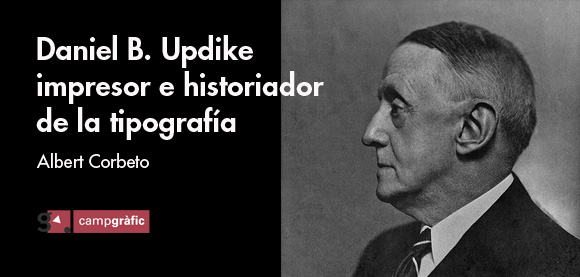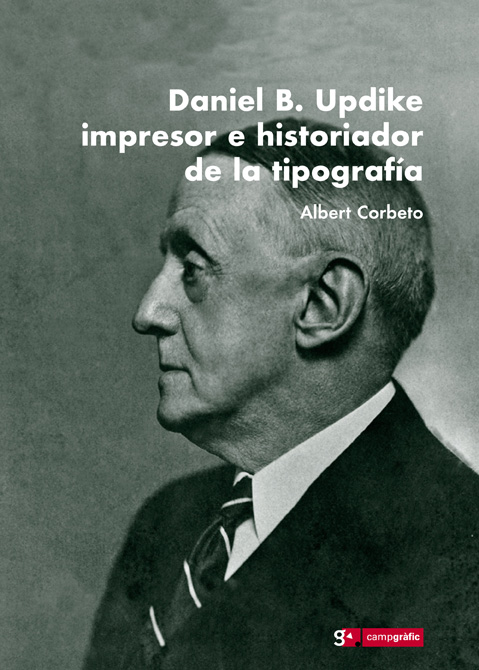
El investigador e historiador de la tipografía Albert Corbeto ha publicado en la Editorial Campgràfic sus dos últimas obras: Daniel B. Updike impresor e historiador de la tipografía y Tipos de imprenta en España. La primera reflexión que se me ocurre es la de que ver el nombre de Updike en la portada de un libro en castellano dice mucho del estado actual e interés creciente de los estudios sobre la historia de la tipografía.
Además Campgràfic ha «tirado la casa por la ventana» y ha puesto en el mercado las dos obras de forma conjunta e inseparable posibilitando apreciar de manera más nítida la importancia del trabajo de Corbeto en el panorama de la investigación histórica sobre nuestro pasado tipográfico. En esta entrada vamos a comentar el libro de Updike dejando para una próxima el que versa sobre los tipos de imprenta en España.
Para todos aquellos que se han interesado por la historia general de los tipos de imprenta, el nombre de Daniel B. Updike remite inmediatamente a una de las «biblias» de la materia su monumental obra Printing types. Their history, forms and use publicado por primera vez en el año 1922. La extensión de la misma, que abarca en sus contenidos centrales la producción tipografía de los principales países europeos desde el periodo incunable hasta el siglo XIX, es de una riqueza y de una utilidad que bien podemos suscribir la idea expresada por Robin Kinross en su Imprenta moderna de que «En lo que respecta a los historiadores de la tipografía, se puede decir que hay un antes y un después de Updike».
En la edición que nos ocupa, el autor ha incluido la traducción literal de los dos capítulos dedicados a los tipos españoles y, lo que a nuestro juicio dota a la misma de un gran valor, tres ensayos en los que Corbeto pone en contexto la obra del norteamericano en toda su extensión enfocando tanto su producción propia en la Merrymout Press como su labor como historiador de la tipografía.
El primero de ellos lleva por título Daniel B. Updike el impresor erudito, y en el mismo el autor nos detalla su biografía desde su nacimiento y sus primeros pasos en el mundo de la imprenta hasta llegar a su consolidación como impresor de renombre. Con un acercamiento crítico a su obra que repasa sus influencias y la evolución de su estilo, el ensayo nos sumerge en el apasionante momento en el que las máquinas irrumpen en los talleres de imprenta a finales del siglo XIX y las poderosas fuerzas que desataron, tanto a favor como en contra, en el mundo editorial. A través de la aptitud de Updike al respecto, Corbeto nos pinta un poderoso «fresco» de la época que, en definitiva, fue una parte fundamental de la historia general de la imprenta.
El segundo ensayo Printing Types. La biblia de los impresores, se centra en la importancia, alcance y repercusión internacional del título capital de la obra de Updike y, lo que a mi juicio es más importante, nos muestra la manera en la que Updike a través de los materiales concretos del oficio como son las muestras de tipos de letras, articula toda una historia de la tipografía que va a significar una consolidación definitiva para una nueva rama de la bibliografía que liderada por los historiadores de la imprenta se había abierto camino desde finales del siglo XIX.
Asimismo en sus páginas encontraremos un detallado recuento de las vicisitudes y convulsiones que sufrió el mundo de la imprenta con la introducción de las máquinas de composición monotipia y linotipia y la influencia que tuvieron en el periodo mágico de «excitación tipográfica» del primer tercio del siglo XX consecuencia de la necesidad de llenar con nuevos diseños sus almacenes de matrices y la importancia que tuvo el libro de Updike como «guía» para esta búsqueda.
Por último, El hispanismo romántico de Updike se centra en la peculiar relación que el impresor e historiador norteamericano mantuvo con España y que se refleja en el entusiasmo que sobre la imprenta española reflejan las páginas de su obra. En este caso Corbeto indaga sobre la percepción de España del autor de Printing Types y encuentra su origen en los libros de viajes de los viajeros anglosajones del siglo XIX que pintaron una España con un retraso atávico respecto al resto de Europa, con sus costumbres peculiares e impregnada del halo romántico que personajes como Lord Byron habían popularizado entre gitanas imponentes y recios bandoleros. Una reflexión que entronca directamente con la historia de España y las particulares circunstancias que marcaron su historia contemporánea.
En definitiva, Daniel B. Updike impresor e historiador de la tipografía, es una obra que pone a disposición de historiadores, diseñadores gráficos y todo aquel interesado en la historia de la tipografía, un material clásico que forma parte de uno de los libros capitales sobre el tema, pero, sobre todo, nos ofrece de la mano de Albert Corbeto una completa perspectiva de un autor y su época dentro del fascinante mundo de la historia del arte que deja constancia de todas las demás, la imprenta.